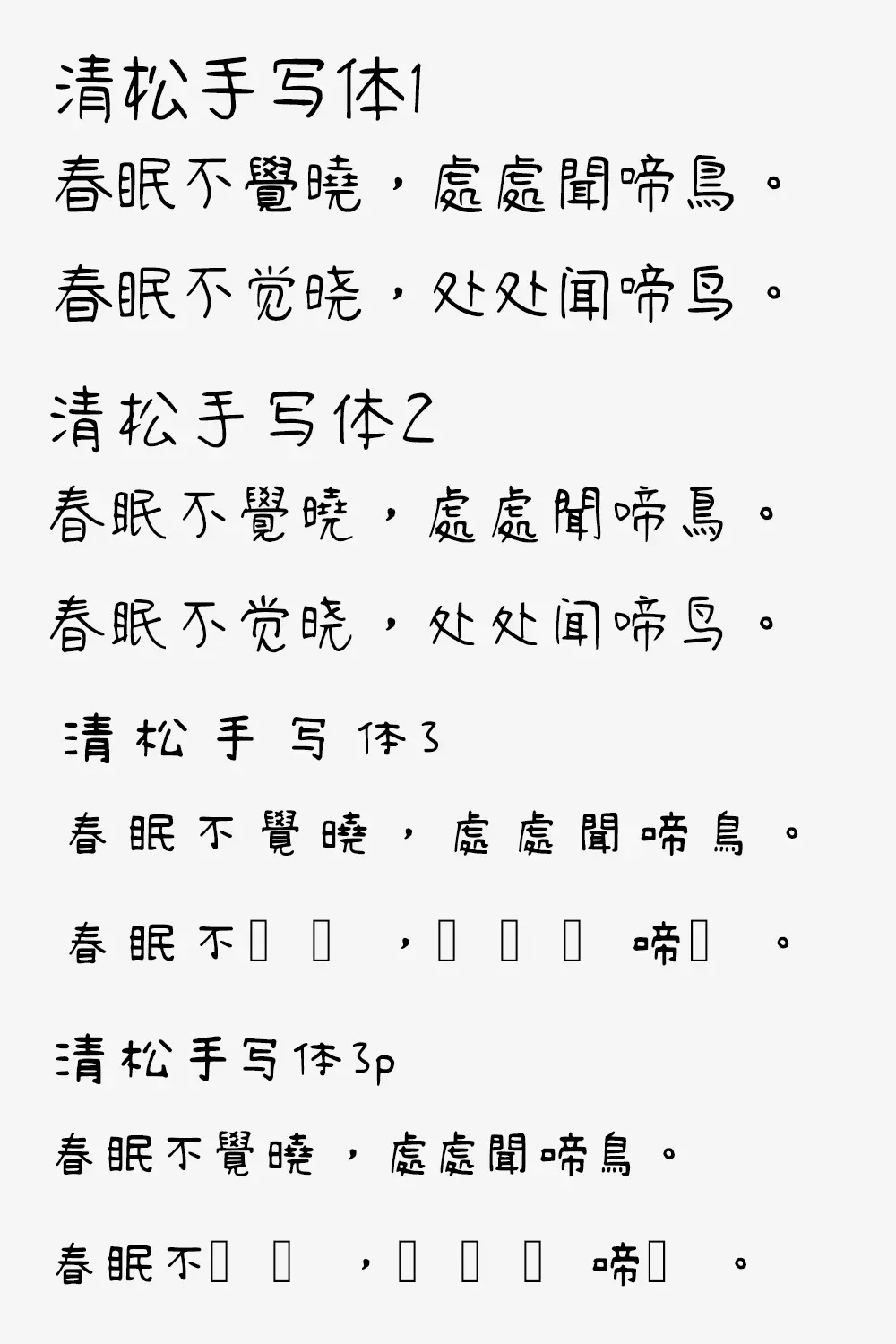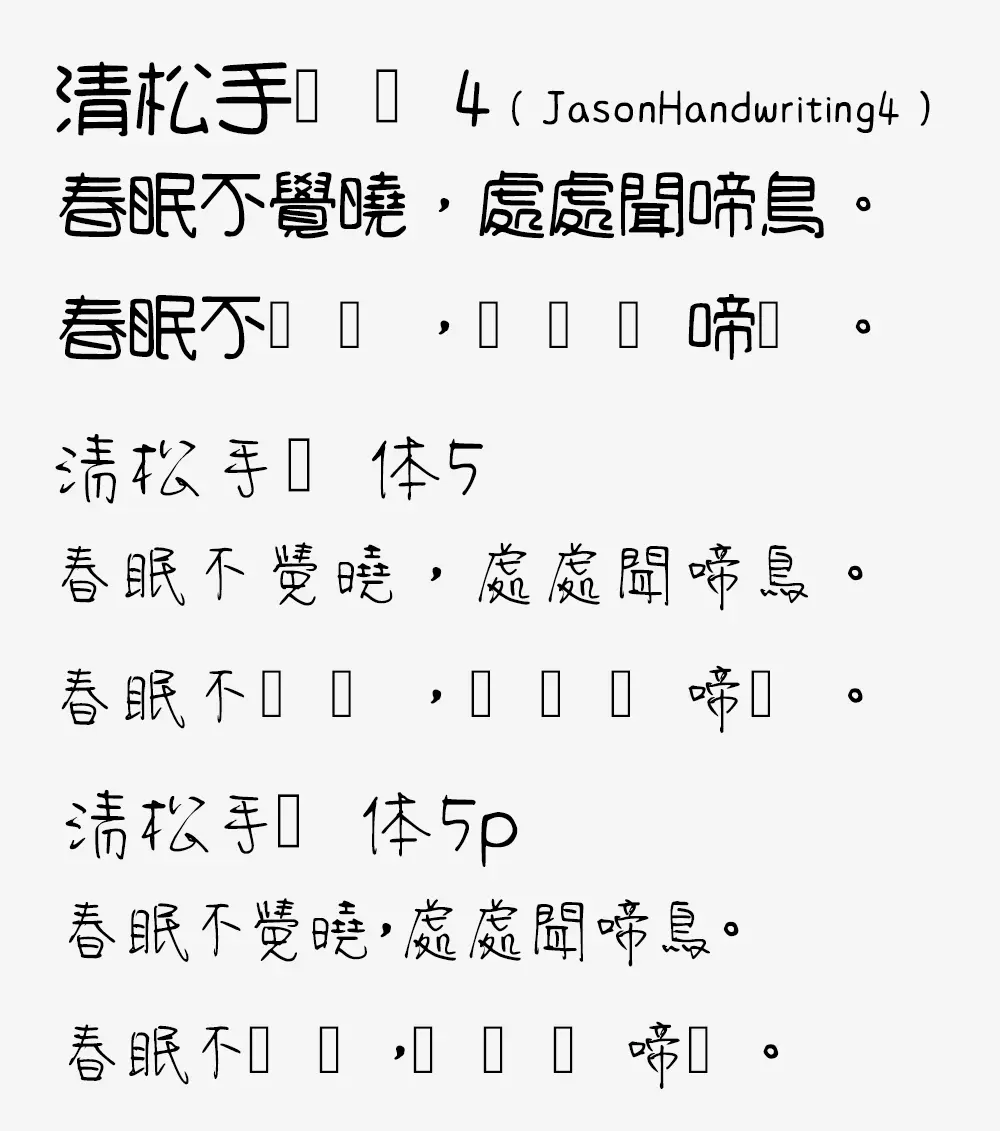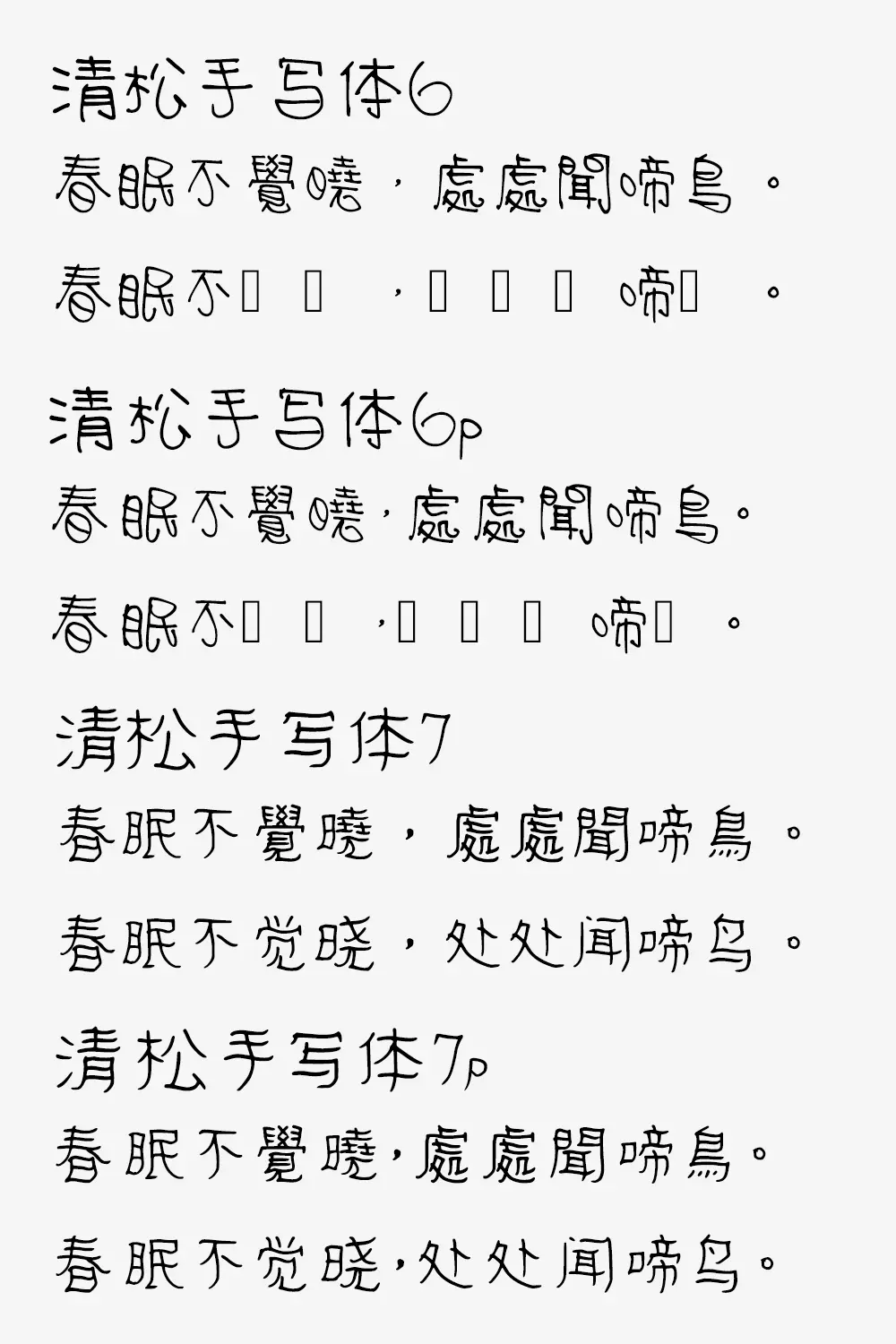
清鬆手寫體是遊清松在稿紙上用原子筆手寫,透過「守寫字」網站產生出初稿字型檔,再透過字型軟體後製作加工而成的手寫字型。
特色:世界上唯一可以讓用戶無條件提出增字要求的免費字型!持續更新、持續創作!個人/企業使用完全免費!任何類型的競爭,只要是合法的也100%完全免費!目前已經釋出5套不同風格的清鬆手寫體
Max修改版是臺灣網友在原版基礎上進行了一些修改,目前修改清鬆手寫體的3個字體,分別是基於這幾個版本:
「清鬆手寫體1」ver 1.48,Max增加(或更新)中文9,836字,增加符號4,802字,目前總字約:25,689字(和符號)。
「清鬆手寫體2」ver 1.06,Max增加(或更新)中文13,322字,增加符號5,339字,目前總字數:26,037字(和符號)。
「清鬆手寫體3」ver 1.24,Max增加(或更新)中文12,167字,目前總字數:17,357字(和符號)。
「清鬆手寫體4」ver 1.01,Max增加(或更新)中文7,383字,目前總字數:18,157字(和符號)。
「清鬆手寫體5」,直接搬原作者的來,沒修改。
附註1:由於是「非原作者」的補字,新加入的字在風格上,雖然盡力求一致,難免會與原作者會有一些不同。
附註2:Max修改的版本,大約有1/10的補出來的字是長的很醜的,不過聊勝於無。
附註3:清鬆手寫體4使用由cjkFont所製作的「cjkFonts手寫4」應該會是更好的選擇,原因是「文字部件的比例」、「筆畫和線條粗細」、「各文字之間中宮鬆緊比例」都較優。
說明:版本編號的前面2碼會是清鬆手寫體原本的版號,第3碼是Max增修的版號。
沒有一般計算機字型的生硬感,多了幾分手寫般的自然感。不論是中文、英文、符號數字,適合在計算機屏幕上閱讀、排版,打印出來效果也很棒的!